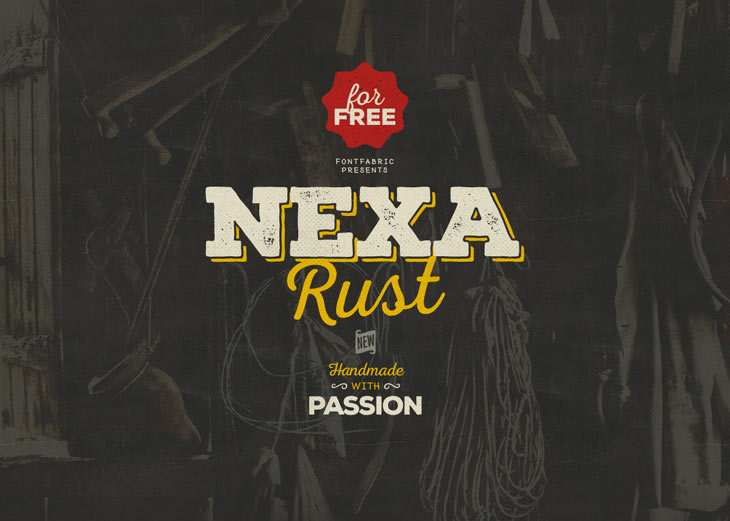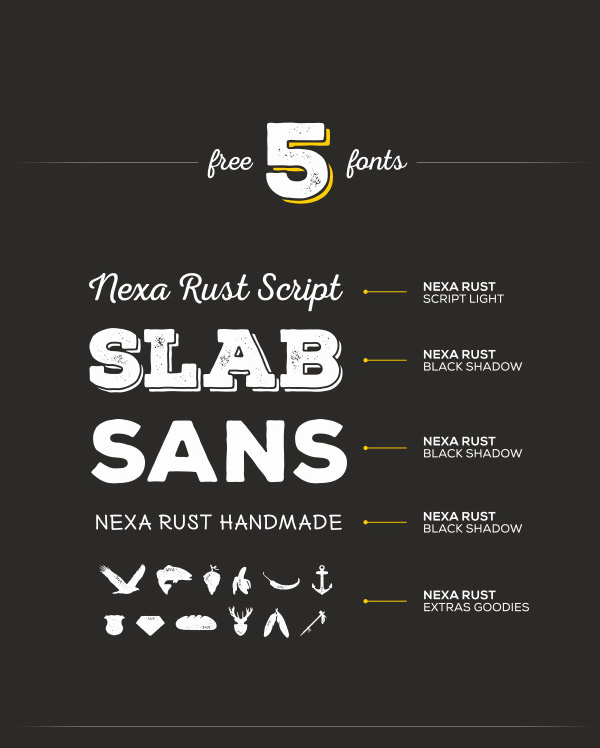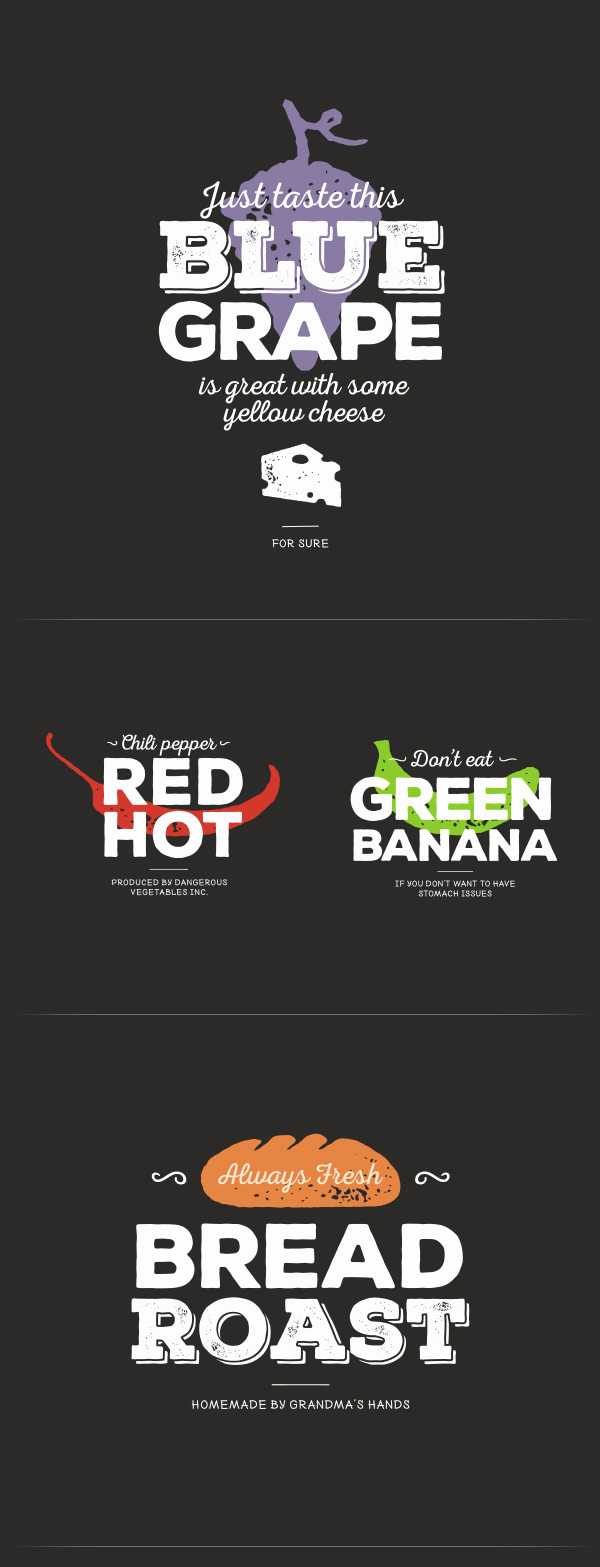
Nexa Rust es la elegida para hoy. Un sistema multifacético de fuente que consiste en varias subfamilias. Gracias a los diseñadores Radomir Tinkov, Svetoslav Simov, Ani Petrova & Vasil Stanev de Font fabric por regalarnos estas 5 fuentes de un total de 83 que se compone la fuente de pago.